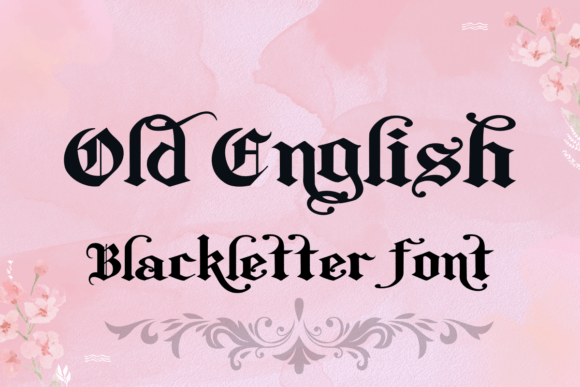
Old English
Old Englishのような高品質の素材をお探しの場合、このプレミアムパッケージはクリエイティブなプロジェクトに素晴らしい選択です。
POD(オンデマンド印刷)製品、結婚式の招待状、またはソーシャルメディアのグラフィックを作成している場合でも、Old Englishは理想的です。